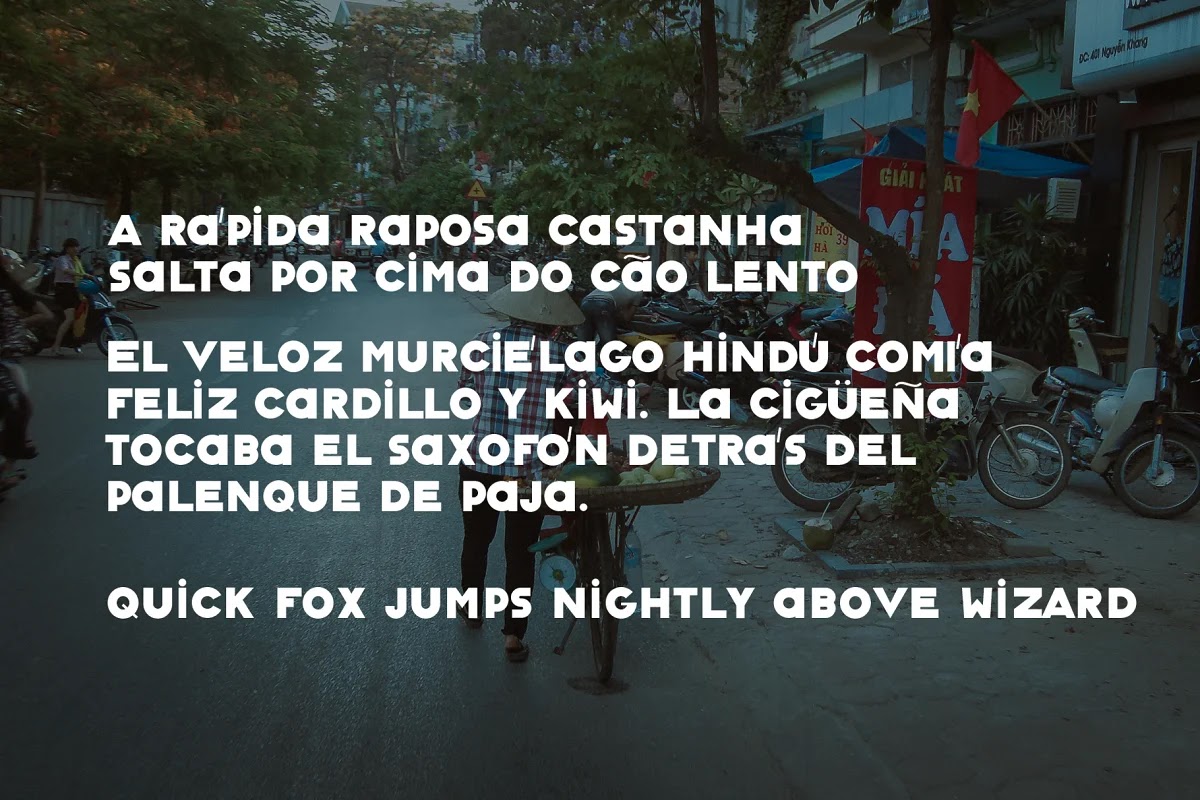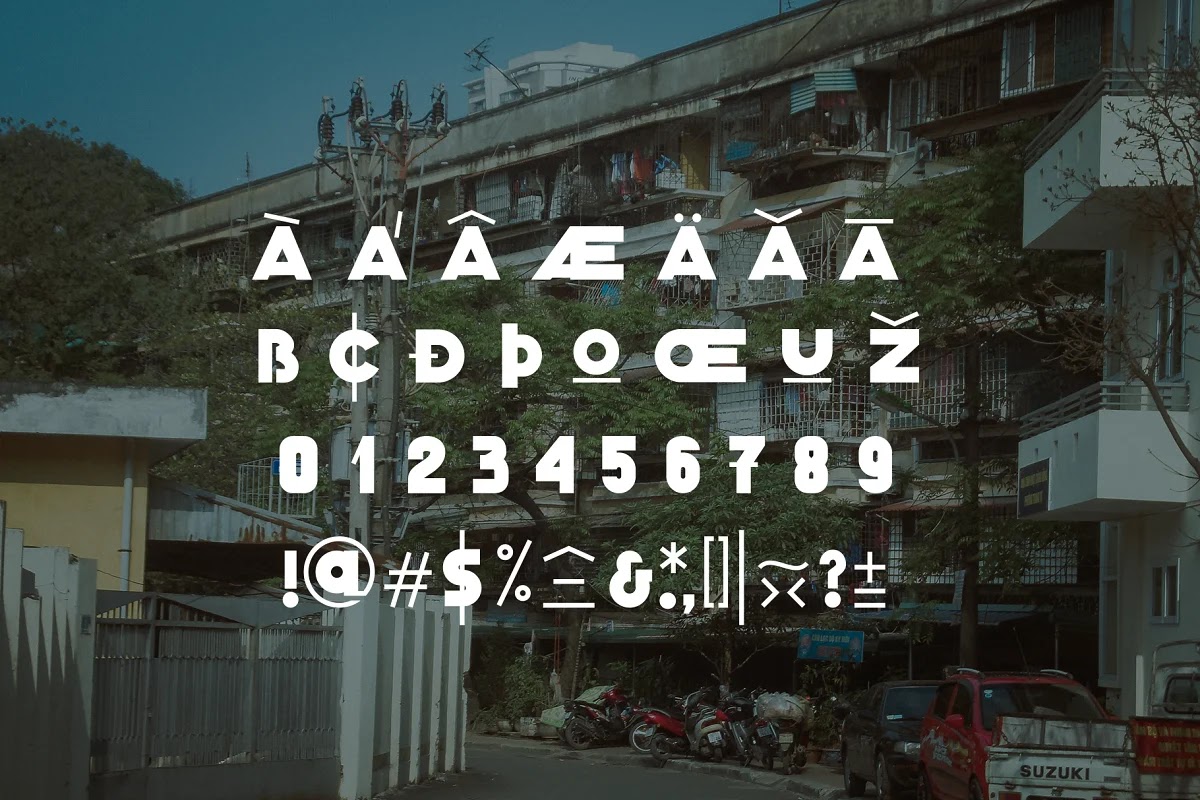
Classique Saigon Typeface là một font được tạo ra bởi Mạnh Nguyễn, một dạng font cổ điển vẽ tay ở Việt Nam từ thế kỷ trước - đặc biệt là ở Sài Gòn. Tác giả lấy cảm hứng từ một dự án mang tên Lưu Chữ (The Lost Type Vietnam - #luuchu), tập trung đáng kể vào những bức ảnh ghi lại từng khoảnh khắc trên đường phố khắp Việt Nam với những biểu ngữ, pa-nô phong cách Sài Gòn này để truyền bá thế giới về điều này Phong cách vẽ tay truyền thống đẹp của Việt Nam và để bảo tồn những nét vẽ ngày càng hiếm hoi.